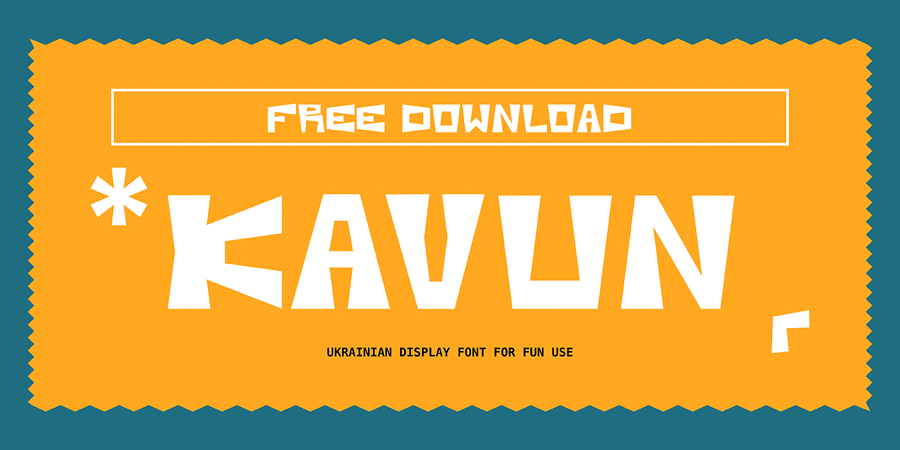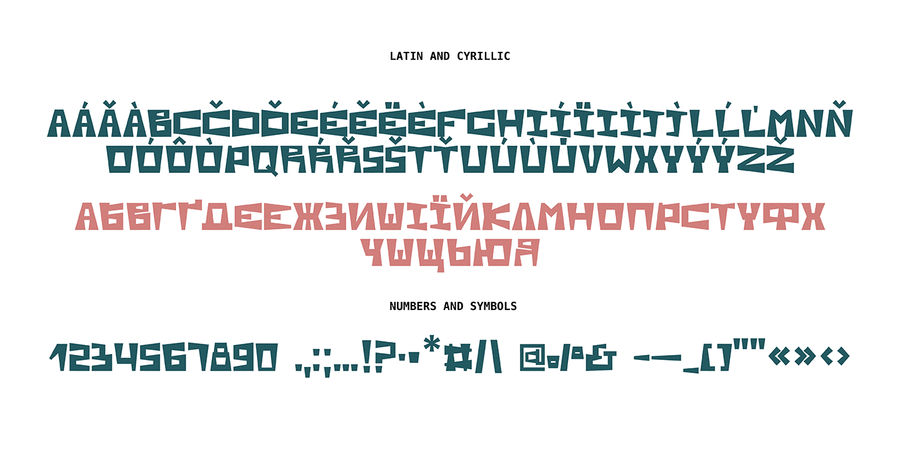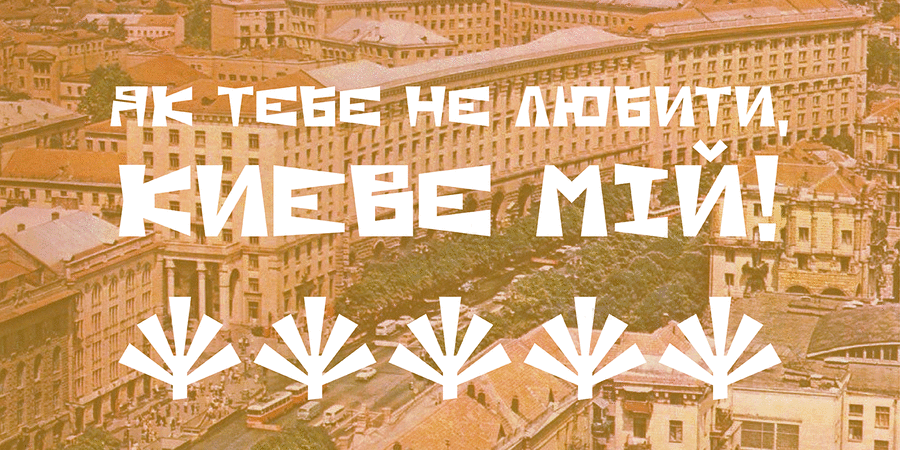
Опис шрифта KavunЦе безкоштовний шрифт, оснований на роботі з паперовою аплікацією. У шрифті літери мають універсальну висоту і позбавлені виносних елементів. Також у формі літер простежується вплив модульних шрифтів. Кавун найкраще підходить для дизайнів крафтових упаковок, флет ілюстрацій, постерів, обкладинок книг з дотепним характером. Шрифт розробила Анна Коваленко у 2023-му році.
плакат, реклама, журнал, пакування, стінгазета, відео, етикетка, обкладинка, афіша, стікер, наліпка, мультфільм, листівка, анімація, комікс Адаптованість гарнітури до носіїв:
Асоціації з сімейством шрифтів KavunОсобистість і характер гарнітури:
іронічний, карикатурний, екстравагантний, чіткий, наполегливий, громіздкий, дивний, характерний, оригінальний, епатажний, експериментальний, яскравий, активний, важкий, твердий, гучний, помітний, нав'язливий, гострий, екстремальний, сміливий, ризикований, вуличний, мотивуючий, зухвалий, хуліганський, кричущий, грубий, ігровий, тусовочний, двіжняковий, ламаний, південний, прикольний, молодіжний, виразний, артистичний, грайливий, смішний, дотепний, мультяшний, студентськиий, радикальний, нахабний, святковий, веселий, жартівливий, комічний, дитячий, наївний, літній, рубаний, запальний, вернакулярний